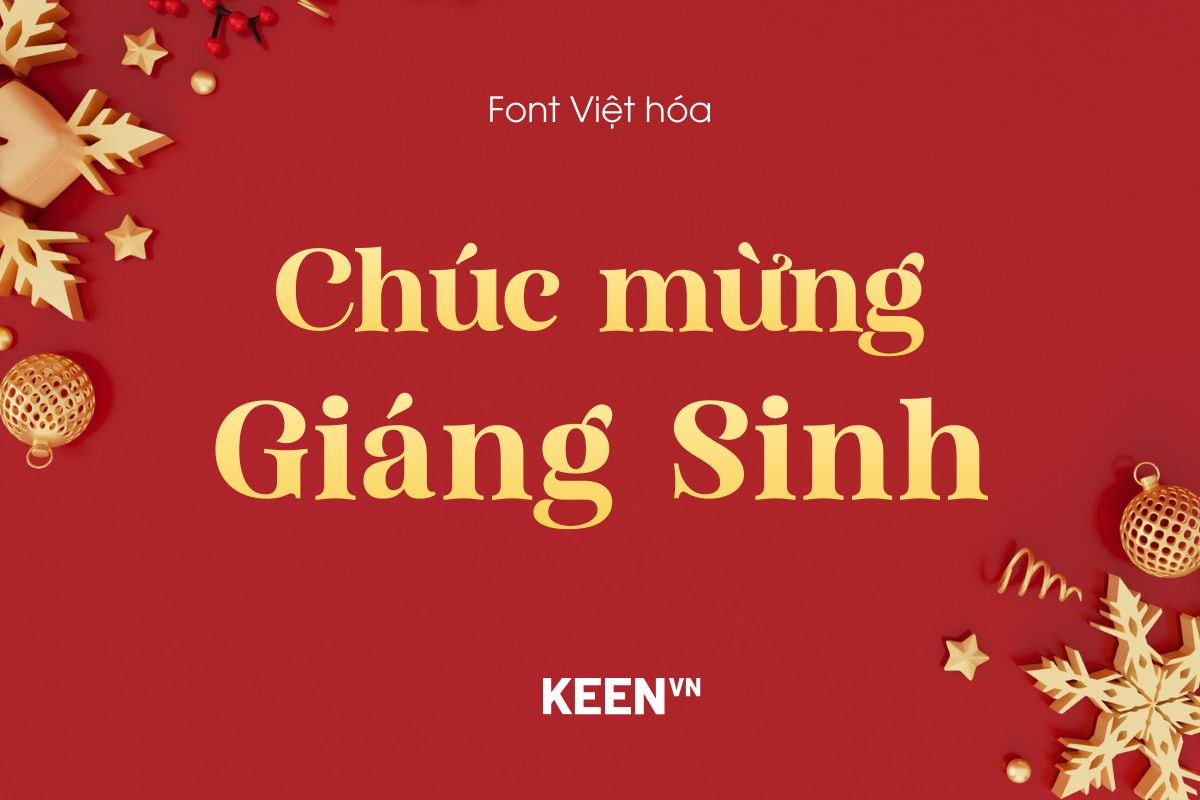
Font Việt hóa DVN Amoitar Regular
• Hỗ trợ đầy đủ dấu tiếng Việt
Font Việt hóa DVN Amoitar Regular mang đến một cảm giác tinh tế ngay từ những đường nét đầu tiên, như một làn gió thanh lịch thổi qua các thiết kế hiện đại. Đây là một kiểu serif đầy quyến rũ với những đường cong mềm mại và dáng chữ uyển chuyển, tạo nên sự cân bằng hài hòa giữa tính cổ điển và sự sang trọng đương đại. Mỗi ký tự trong Amoitar được chăm chút tỉ mỉ, từ độ dày mỏng của nét chữ đến khoảng cách chữ được tính toán cẩn thận, khiến toàn bộ bộ font trở thành một tác phẩm nghệ thuật hơn là chỉ một công cụ thiết kế.
Amoitar Regular sở hữu khả năng ứng dụng rộng rãi, phù hợp cho cả thiết kế in ấn, đồ họa, thương hiệu lẫn các giao diện web cần sự trang nhã. Khi được đưa vào tiêu đề, trích dẫn hay các bố cục mang tính nghệ thuật, font chữ này giúp nội dung trở nên nổi bật với phong thái cao cấp và chỉn chu. Việc font đã được Việt hóa hoàn chỉnh giúp người dùng khai thác trọn vẹn vẻ đẹp của nó trong các dự án tiếng Việt mà không lo mất đi tinh thần thẩm mỹ ban đầu.
Sử dụng DVN Amoitar Regular, bạn không chỉ thêm một kiểu chữ vào bộ công cụ sáng tạo của mình, mà còn đưa vào dự án một cảm xúc sang trọng, mềm mại và đầy tinh thần nghệ thuật. Đây là lựa chọn lý tưởng cho những ai muốn mang đến sự đẳng cấp và nét đẹp tinh tế cho từng thiết kế – từ thương hiệu, poster, bao bì cho đến các trang web mang phong cách hiện đại.